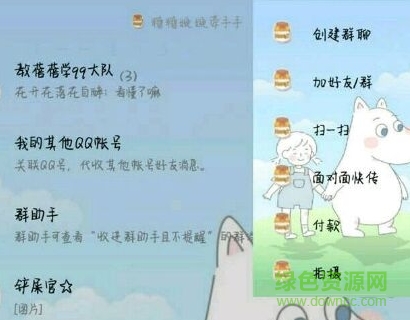
神韻美麗手跡體是一款全新的神韻字體,字跡連貫卻不進(jìn)走,給人恣意優(yōu)雅的外觀形態(tài),讓人看起來十分舒適,無論是文章閱讀還是內(nèi)容書寫都很不錯(cuò),更多精彩請(qǐng)來綠色資源網(wǎng)下載體驗(yàn)吧!
神韻美麗手跡字體是即神韻浪漫情書體后推出的手寫字體,給大家?guī)砀噙x擇和視覺享受,中英文都有其特色,可以運(yùn)用在藝術(shù)設(shè)計(jì)、廣告創(chuàng)意、平面設(shè)計(jì)、創(chuàng)意海報(bào)等多個(gè)領(lǐng)域。